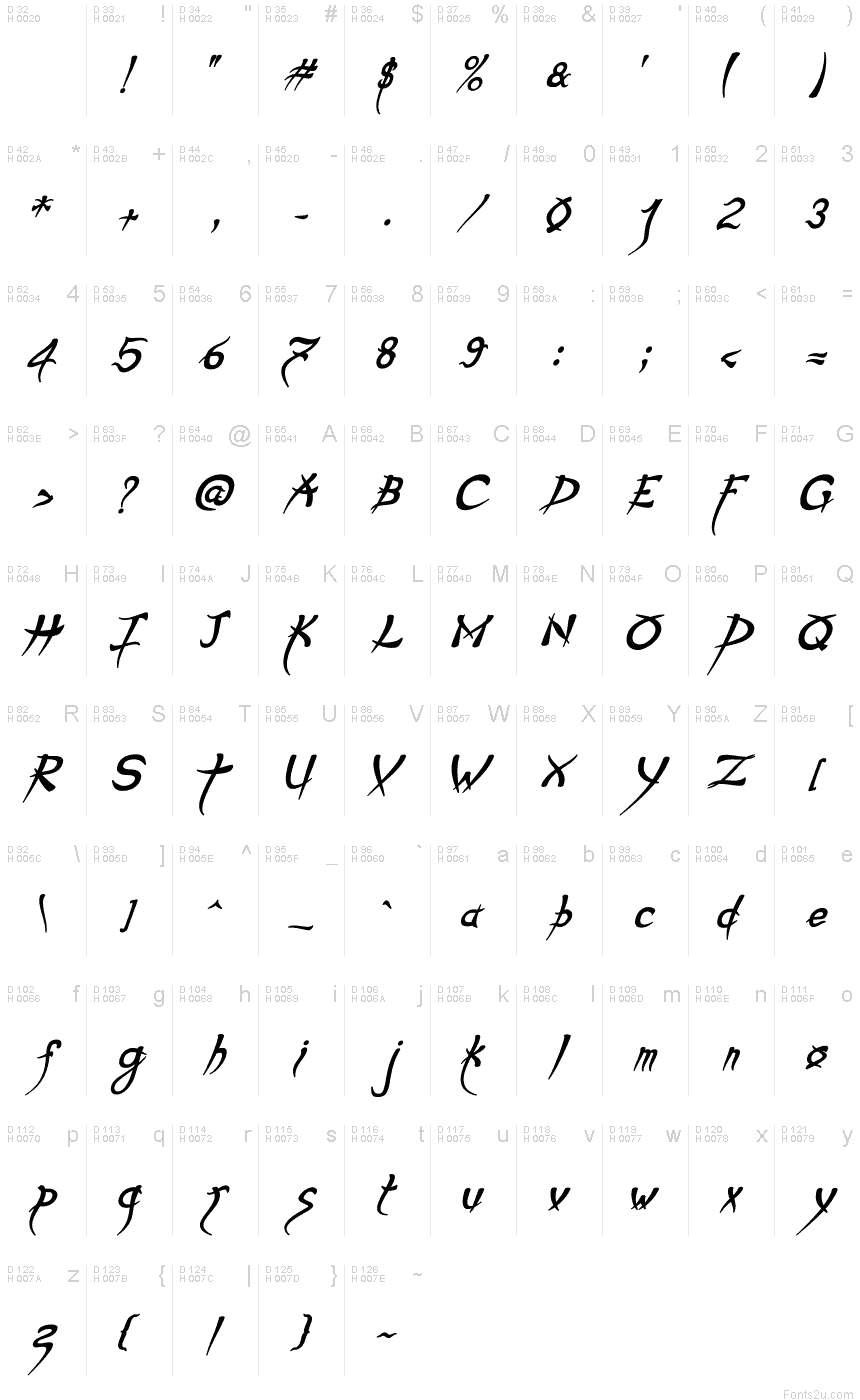
Psycho Bold Italic 字体
Psycho 字体家族,包含 4 款字体
Psycho Bold Italic
Remy Demarest
由 Remy Demarest 设计的 Psycho Bold Italic 是一款免费的漫画展示字体,它以锋利的笔触和狂野的前倾姿态横扫页面。Psycho 系列的粗体斜体字看起来像是一气呵成的狂乱之作——笔画扭动、钩连、翻飞,带着一种不稳定的能量,即便在超大字号下依然保持着惊人的易读性。它充满了墨迹感、喧闹感,甚至带有一丝疯狂,为标题赋予了一种普通漫画字体难以企及的手绘恐慌感。
使用 Psycho Bold Italic,你可以为恐怖海报、惊悚小说封面、前卫漫画标题、鬼屋传单、乐队标志以及吸睛的 YouTube 缩略图增添十足的戏剧张力。这款免费字体在需要体现紧迫感、危险感或略微失衡的视觉效果时表现卓越。建议将 Psycho Bold Italic 与简洁的无衬线窄体字搭配用于正文,从而将混乱的视觉中心完全锁定在你的标题或主标语上。